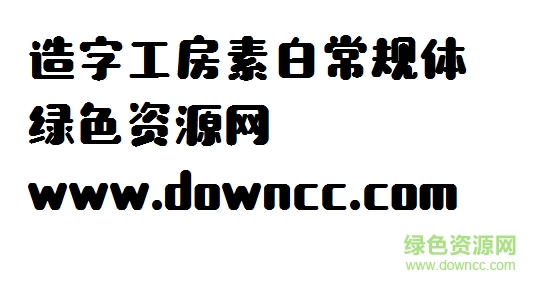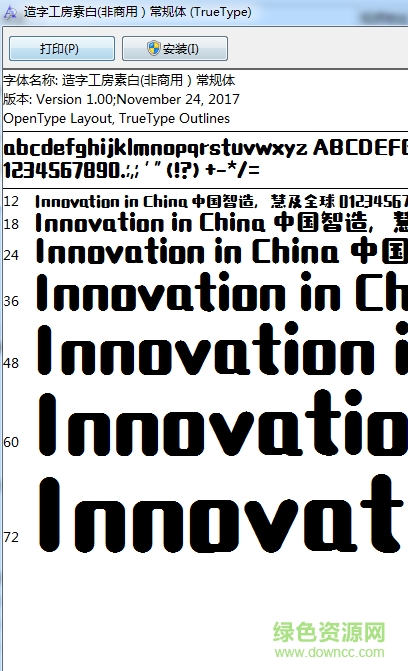
造字工房素白常規(guī)體是一款風格圓潤的字體,素白體沒有僵硬的棱角,給人非常清新柔和的感覺,整體效果呆萌好看,歡迎到本站下載使用!
造字工房素白體字體是一款應用于藝術設計方面的簡體中文字體,該字體筆畫粗壯,大字效果突出且引人注目;并且最大程度還原作者書寫字形,細節(jié)表現(xiàn)完整,且字庫完整,可以廣泛應用于名片設計、新聞媒體、宣傳海報、ppt、影視制作以及內容用字等領域。